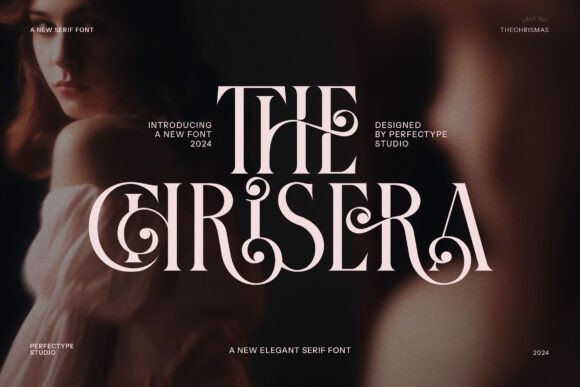
The Shrisera
適切なデザイン要素を見つけるのは難しい場合がありますが、The Shriseraは作品を即座に引き立てる優れたコレクションを提供します。
POD(オンデマンド印刷)製品、結婚式の招待状、またはソーシャルメディアのグラフィックを作成している場合でも、The Shriseraは理想的です。